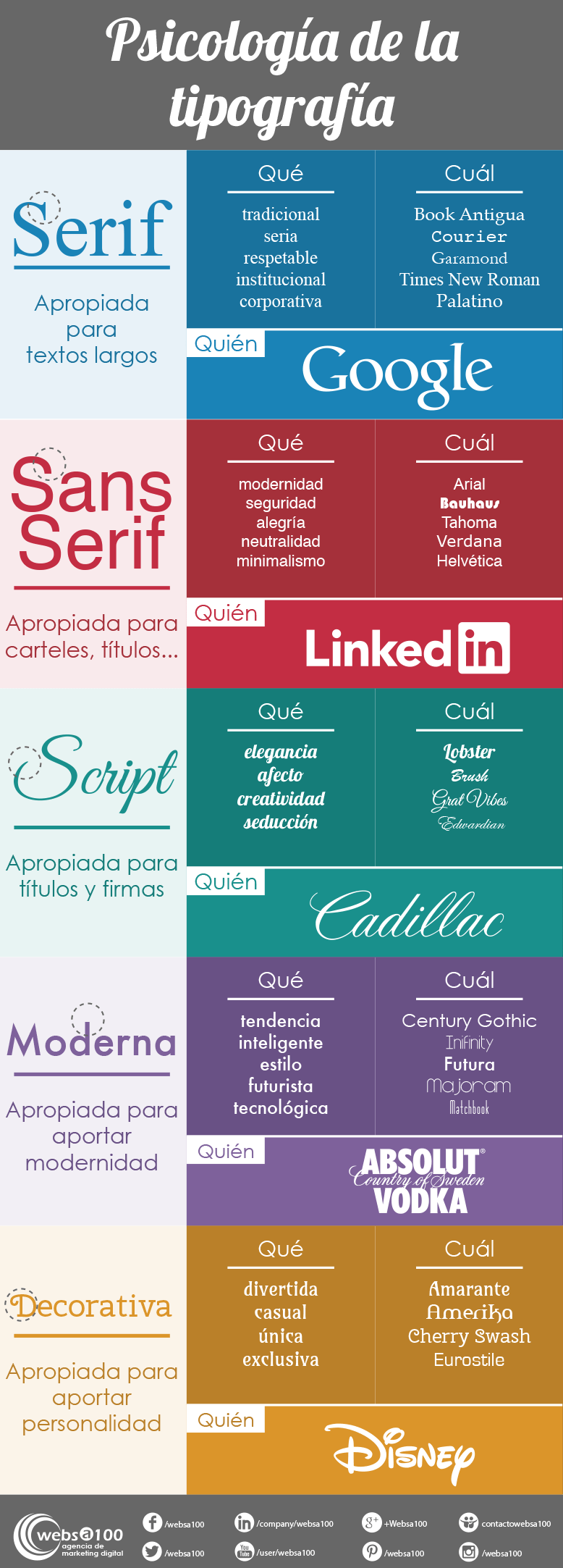
Conocer la psicología de la tipografía es disponer de un arma a nuestro favor.
A la hora de diseñar un logotipo, lo primero que debemos hacer es pensar lo que pretendemos transmitir con él y dejarlo muy claro. Una vez tengamos esto definido, deberemos elegir los colores y tipografías que vayamos a utilizar en nuestro logo. Es aquí donde, como sucede con los colores, entra en juego la psicología de la tipografía, ya que simplemente con mirar un tipo de letra sentiremos involuntariamente una emoción.
Conocer lo que transmite cada familia tipográfica puede sernos de gran ayuda, ya que esos conocimientos los podremos aplicar para elegir la fuente que potencie aquello que nosotros queremos transmitir de nuestro negocio.
Por el contrario, una mala elección de la tipografía de nuestro logo puede hacer que el conjunto no sea efectivo, que transmitamos algo completamente opuesto a lo que pretendíamos, y no llegar así a nuestro target.
Por ejemplo, imaginemos el logotipo de Microsoft con la tipografía de Coca-Cola, o el logotipo de Google con la de Instagram. Ninguno de ellos funcionaría demasiado bien.
Microsoft utiliza una fuente Sans-serif que, como vemos en la infografía, transmiten modernidad y seguridad. Google una Serif que nos sugiere estabilidad y fiabilidad y, tanto Coca-Cola como Instagram, utilizan tipografías del tipo Manuscritas o Script que asociamos a la creatividad, elegancia y afecto.
Así que, para que conozcáis las emociones que transmite, y a lo que asociamos inconscientemente cada familia tipográfica, os traemos esta infografía sobre psicología de la tipografía, en la que además añadimos los nombres de algunas fuentes de cada familia para que sepáis cuales utilizar.